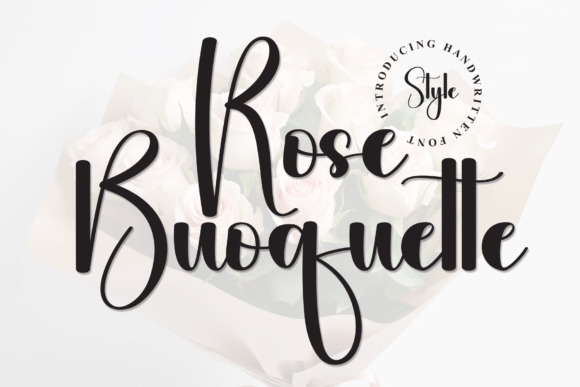
Rose Buoquette
Rose Buoquetteのような高品質の素材をお探しの場合、このプレミアムパッケージはクリエイティブなプロジェクトに素晴らしい選択です。
POD(オンデマンド印刷)製品、結婚式の招待状、またはソーシャルメディアのグラフィックを作成している場合でも、Rose Buoquetteは理想的です。